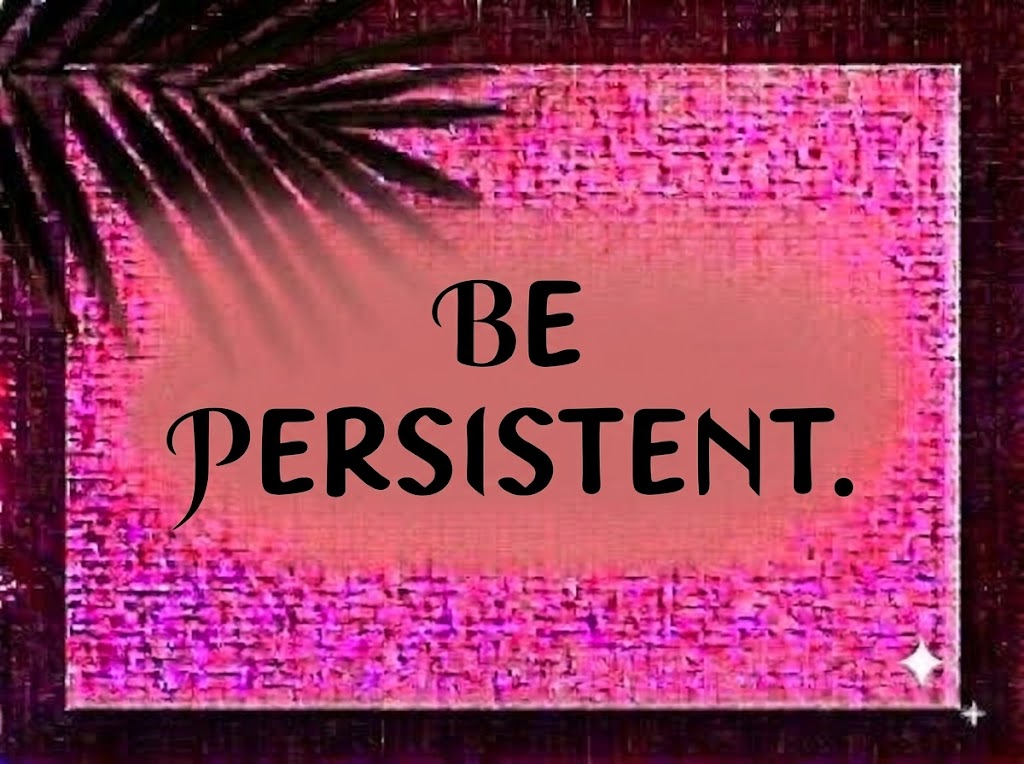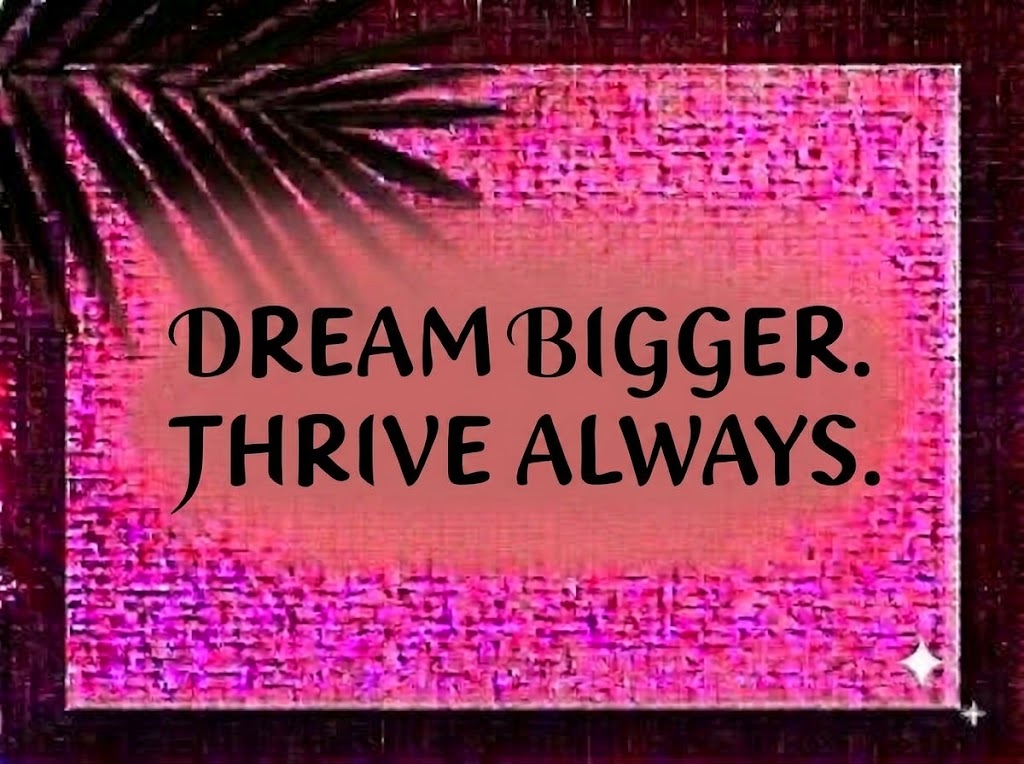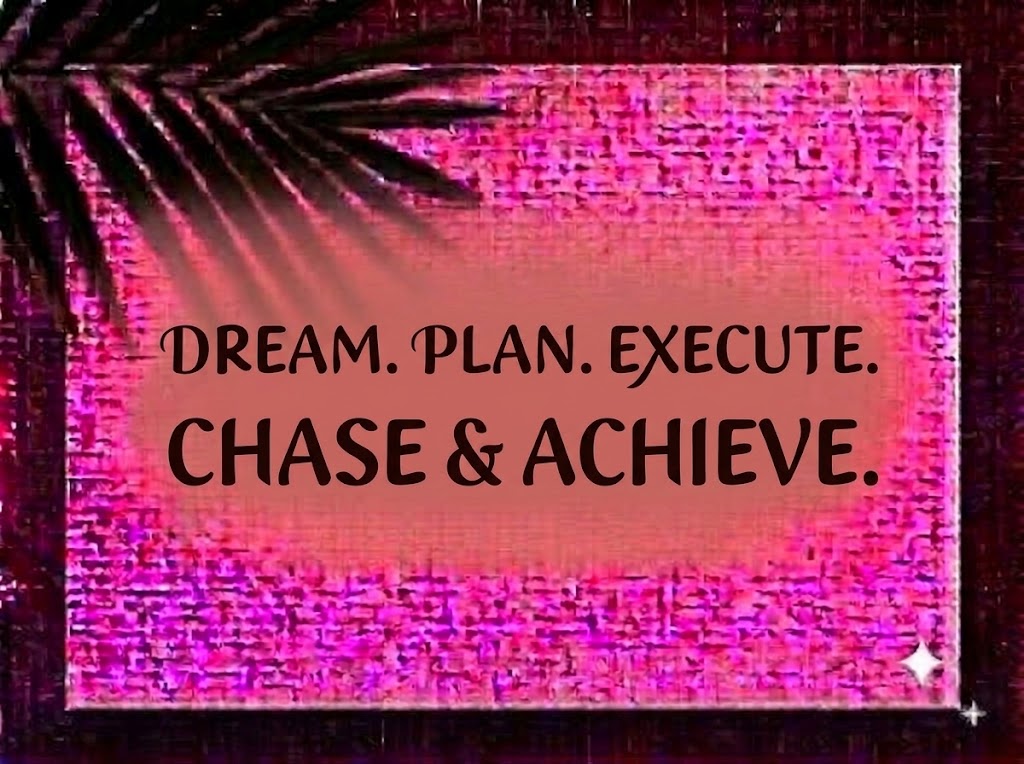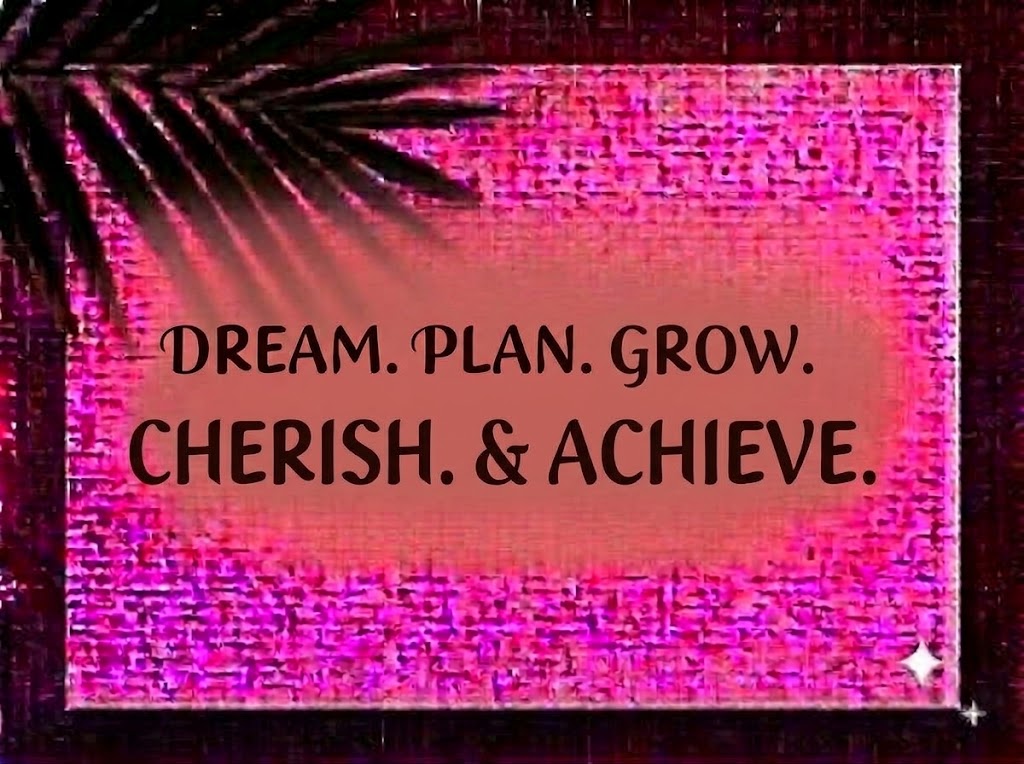
1FTV Maestrale
Trong nghệ thuật thiết kế đồ họa thị giác và dàn trang ấn phẩm, các phông chữ thư pháp mang âm hưởng thần thoại châu Âu (Fantasy / Celtic Calligraphy) luôn đem lại sức quyến rũ đặc biệt. Những con chữ sở hữu nét vươn dài thanh thoát, đường cong uốn lượn mềm mại như những ngọn gió lướt qua trang giấy không chỉ tạo nên bầu không khí cổ tích kỳ ảo mà còn nâng tầm cảm xúc cho toàn bộ tác phẩm nghệ thuật.
Nếu bạn đang tìm kiếm một phông chữ hiển thị độc lạ, đậm chất thơ và huyền bí để thiết kế bìa tiểu thuyết giả tưởng, poster phim kỳ ảo, nhãn rượu vang hay tiêu đề video ngắn triệu view, font 1FTV Maestrale chính là sự lựa chọn không thể bỏ qua.
Giới thiệu về font 1FTV Maestrale
Font 1FTV Maestrale là bộ chữ hiển thị mang phong cách Calligraphic Script pha lẫn tinh thần Fantasy cổ điển, lấy cảm hứng từ những làn gió Tây Bắc lãng mạn của vùng Địa Trung Hải:
Đặc điểm nổi bật của ngôn ngữ thiết kế Maestrale
Sức hút thị giác của font 1FTV Maestrale đến từ sự uyển chuyển tự nhiên của ngòi bút thư pháp cùng những đường nét biến điệu độc bản:
Hơi thở cổ tích & Thần thoại thời Phục Hưng: Cấu trúc chữ gợi nhớ đến những trang sách phép thuật, bản thảo chép tay thời Trung Cổ, vừa kiêu kỳ đài các, vừa mang chiều sâu huyền bí.
Độ tương phản thanh đậm nhịp nhàng: Các trục nét đứng có độ đậm chắc chắn kết hợp khéo léo cùng các nét lướt thanh mảnh như sợi tơ, tạo nên nhịp điệu đọc bay bổng, êm ái mà không bị rối mắt.
Bộ chữ số tạo dáng cổ điển: Dãy số từ 0-9 được tạo tác với những đường nét uốn lượn đồng điệu với dàn chữ cái, giúp hiển thị mốc thời gian hay số chương sách một cách trang trọng.
Tối ưu hiển thị và dấu tiếng Việt từ 1FTV
Để phông chữ vận hành mượt mà trên cả hai hệ điều hành Windows và macOS, phiên bản này đã được xử lý kỹ lưỡng về mặt thông số nội tại:
Khoảng cách ký tự (Kerning): Khoảng hở giữa các chữ cái được tính toán tỉ mỉ, giúp các đường nét vươn dài khi đứng cạnh nhau không bị va chạm hay chồng đè lem nhem.
Hệ thống ký tự đồng bộ: Tích hợp trọn vẹn bộ chữ in hoa, in thường, dãy số 0-9 cùng đầy đủ các ký hiệu toán học và dấu câu cơ bản.
Đánh giá hiển thị thực tế
Khả năng hiển thị của phông chữ được tối ưu linh hoạt theo nhiều kích cỡ:
Kích thước nhỏ (12pt – 24pt): Cấu trúc nét rõ ràng giúp các câu danh ngôn ngắn, lời tựa hay dãy số hiển thị trang nhã trên các trang sách và ấn phẩm in ấn.
Kích thước lớn (36pt – 72pt): Đây là đất diễn lý tưởng nhất để 1FTV Maestrale phô diễn toàn bộ nét uốn lượn kỳ ảo, sự phóng khoáng và thần thái cổ tích cho các dòng headline chính.
Ứng dụng trong thiết kế đồ họa và sản xuất video
Sở hữu nét cá tính huyền bí và giàu chất thơ nghệ thuật, font 1FTV Maestrale mở ra không gian ứng dụng phong phú:
Ảnh thu nhỏ YouTube (Thumbnail): Lựa chọn hoàn hảo cho các kênh kể chuyện kinh dị/kỳ bí, phân tích văn học, âm nhạc Medieval/Acoustic Lofi hay podcast chữa lành nhờ diện mạo nghệ thuật và thu hút.
Bìa sách, Ấn phẩm Editorial & Thiệp cưới: Lựa chọn hàng đầu cho bìa tiểu thuyết Fantasy, thơ ca, thiệp cưới phong cách Vintage/Rustic, menu dạ tiệc sang trọng hay thư mời sự kiện nghệ thuật.